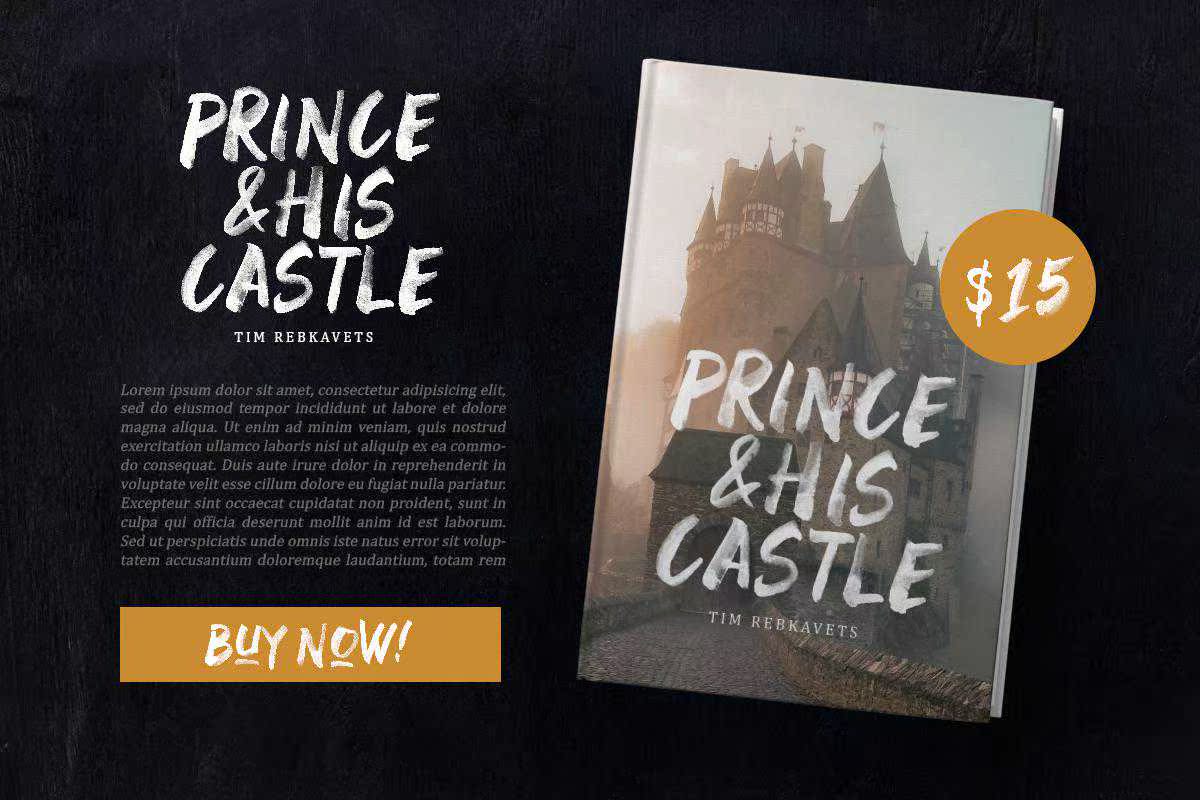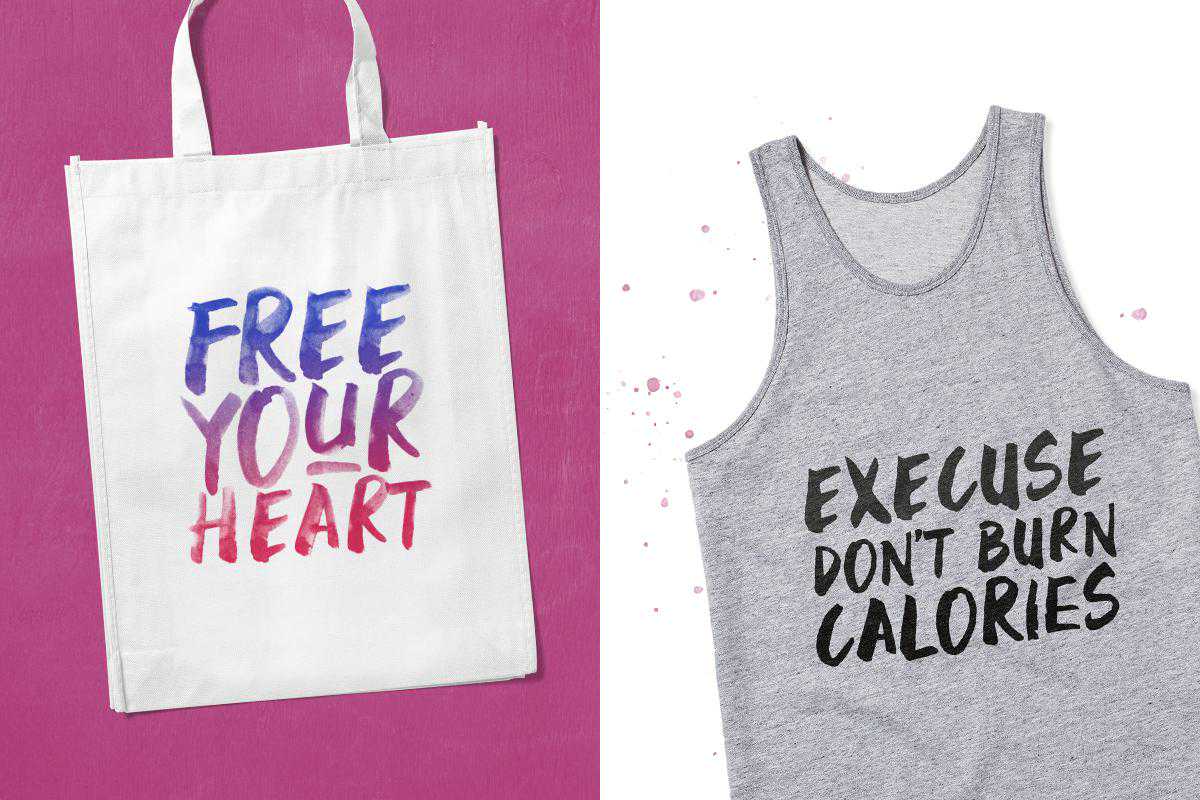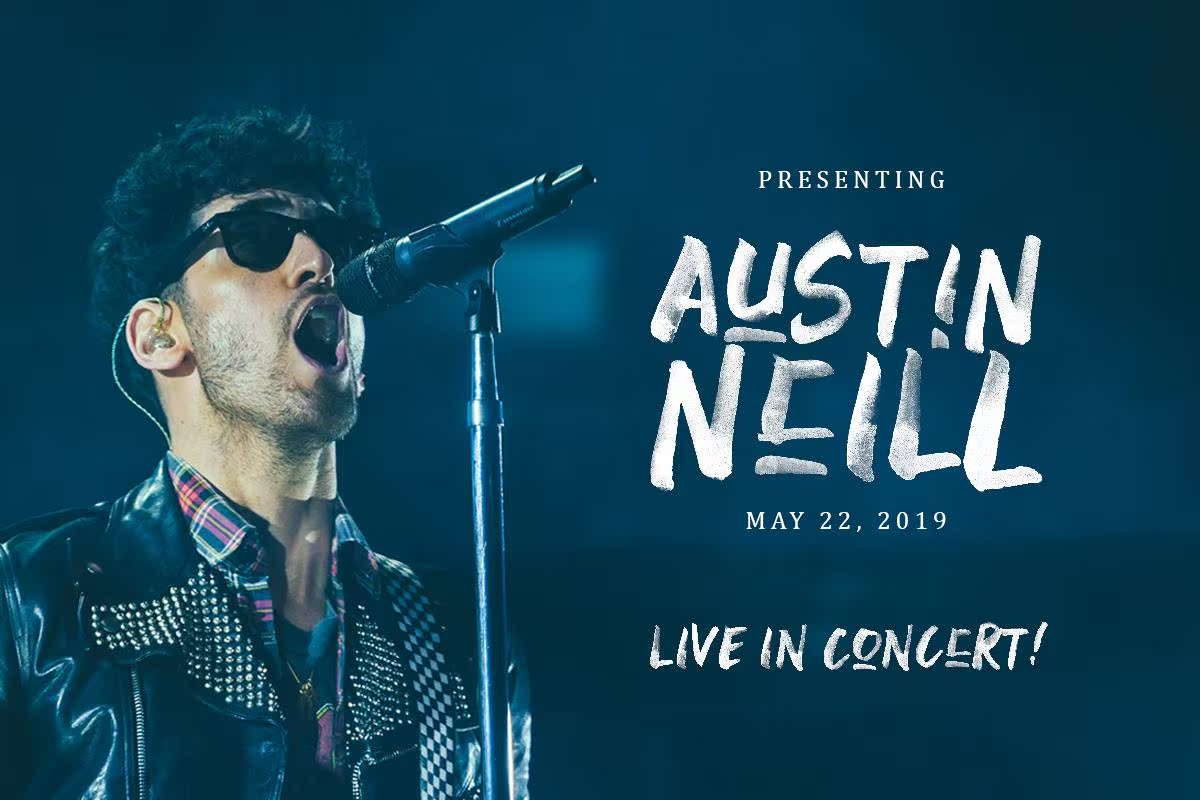
BlackSpace,aSVGFont,采用混合字体书写。自然文字使字体字迹不受拥挤影响。适用于需要字体的用户,如标题、标识、服装、邀请、品牌、包装、广告等。字体包括大写、小写、标点符号、符号和数字、文体设置、连字、,ETCALSO支持多语言。它也采用UAR编码。BlackSpace、aSVGFont、Madebbrush手写。自然文本使字体看起来不拥挤。适用于需要标题、标识、服装、邀请、品牌、包装、广告等字体的用户。此字体包括大写、小写、标点符号、符号和数字、样式设置交替、,连字,etcalsosupportmultilingual.ItalsoalreadyPUAEncoded。